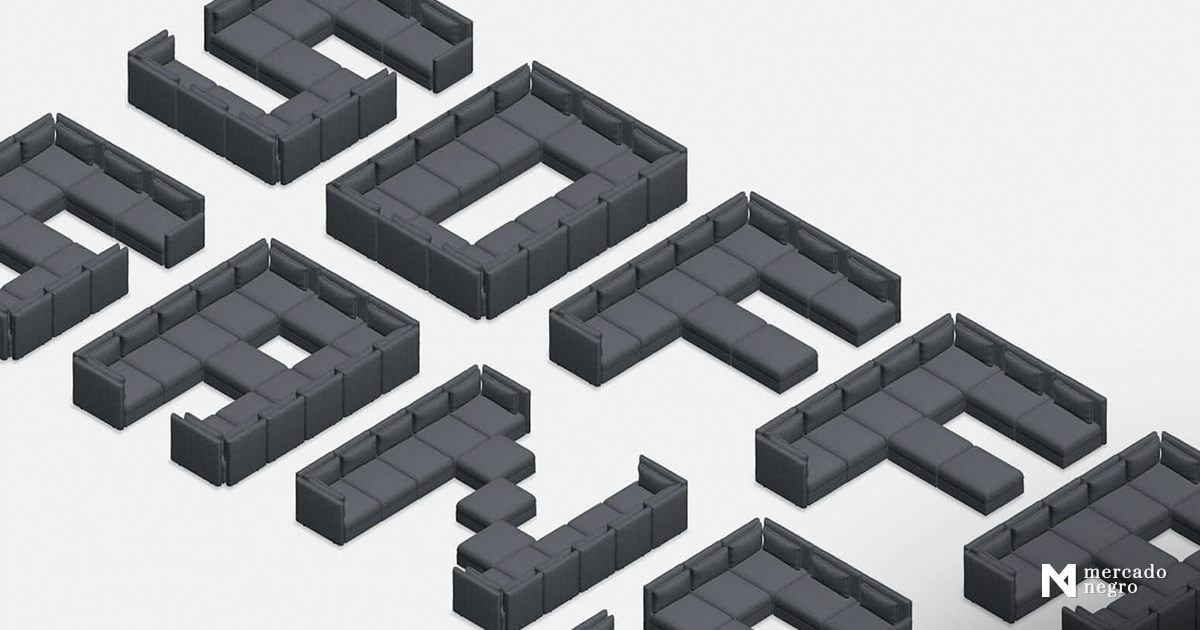
Soffa Sans: La tipografía de Ikea inspirada en un meme
A base de sofás, Ikea creó letras y números en una tipografía gratuita nunca antes vista.
Ikea, firma dedicada a la fabricación y venta de muebles, le dio la vuelta a graciosos memes difundidos en las redes sociales tras el lanzamiento de su herramienta de planificación de sofás.
“Desing your own sofá” es la plataforma de Ikea que le dio el curioso inicio a su nueva tipografía. Resulta ser que los usuarios descubrieron que podían usar perfectamente la herramienta para no solo crear su mueble ideal, sino que también les permitió realizar tantas combinaciones como les fueran posible con formas extrañas y absurdas. Al terminar de crear los muebles, el precio era exorbitante, lo que finalmente originó la burla de muchos usuarios, quienes a base de memes hicieron viral lo sucedido.
A raíz de lo antes mencionado, Ikea optó por utilizar los memes creados por sus usuarios, para desarrollar su creativa estrategia. Es así como, junto a la agencia Proximity London, crearon “Soffa Sans Font”.
La ingeniosa tipografía está disponible en tres colores; azul, blanco y gris; además cuenta con todo el abecedario, números y signos de puntuación. Adicional a esto, tiene dos variantes: una donde se puede apreciar en una vista isométrica y otra con una vista cenital. Soffa Sans Font, es completamente gratuita y se puede descargar en la página de Ikea.
De esta manera, el gigante sueco ha sabido usar el ingenio para hacerse un puesto en la industria, siendo actualmente un referente para muchos usuarios.